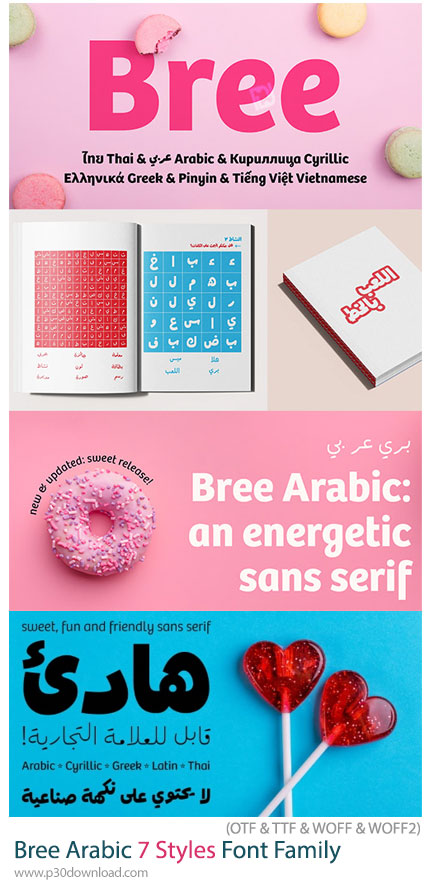
در این بخش شاهد فونت عربی و انگلیسی بر با 7 استایل مختلف می باشید که با فرمت های OTF و TTF و WOFF و WOFF2 و JPG بر روی سایت برای دانلود قرار گرفته است. Bree Arabic 7 Styles Font Family یک خانواده فونت عربی/انگلیسی زیبا و حرفهای است که با طراحی نرم، خوانا و مدرن، گزینهای بسیار مناسب برای انواع پروژههای گرافیکی، تبلیغاتی، چاپی و دیجیتال به شمار میرود. این مجموعه معمولاً شامل 7 استایل مختلف از فونت Bree Arabic است که به طراحان اجازه میدهد در عین حفظ یکپارچگی بصری، از وزنها و حالتهای متنوع برای تیتر، متن، لوگو، پوستر، رابط کاربری و محتوای تبلیغاتی استفاده کنند. اگر به دنبال فونتی هستید که هم ظاهر امروزی و حرفهای داشته باشد و هم در زبان عربی و فارسی از خوانایی خوبی برخوردار باشد، این خانواده فونت میتواند انتخابی کاربردی و ارزشمند برای آرشیو طراحی شما باشد. Bree Arabic نسخه عربی/سازگار با اسکریپت عربی از خانواده فونت Bree است که با حفظ روح طراحی اصلی، برای نوشتار عربی و فارسی بهینهسازی شده است. فرم حروف در این فونت معمولاً ترکیبی از نرمی، صمیمیت، شخصیت بصری مدرن و خوانایی بالا است؛ به همین دلیل در پروژههایی که هم زیبایی و هم وضوح متن اهمیت دارند، عملکرد بسیار خوبی دارد.
کاربردهای این خانواده فونت:
- طراحی پوستر و بنر تبلیغاتی
- استفاده در پست و استوری شبکههای اجتماعی
- طراحی رابط کاربری اپلیکیشن و وب
- صفحهآرایی و طراحی مجلات و بروشورها
- استفاده در تیترها و متنهای تبلیغاتی
- ساخت لوگوتایپ یا هویت بصری برند
- تولید محتوای آموزشی و دیجیتال